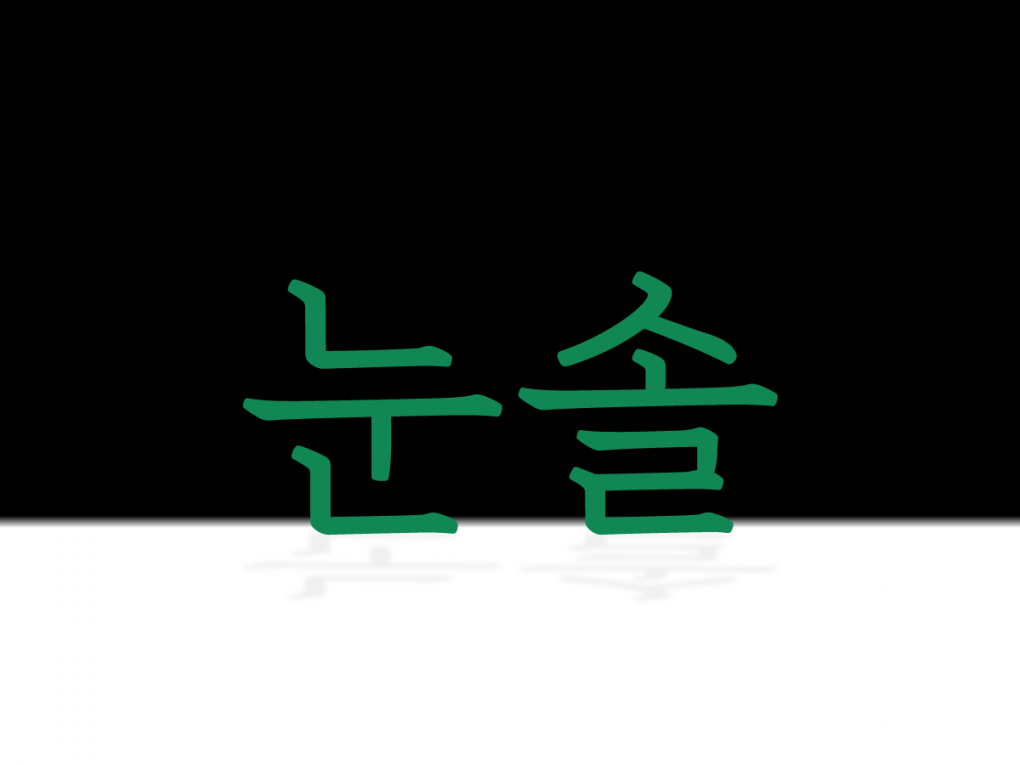
「눈솔」 웨이트 확장에 담긴 숨은 이야기
「눈솔」은 산돌 브랜드사를 이용하는 유저 둘 중 하나는 사용하고 있을 정도로 조용히 강한 폰트입니다. 화려하지는 않지만 묵묵하고 단단한 인상을 가진 「눈솔」 폰트는, 최근 더 넓은 사용성을 위해 확장된 웨이트들로 인사를 드리게 되었어요. (기존 1종(Bold) → 확장 3종(Thin, Regular, Bold))
사실 「눈솔」 폰트는 기획 단계에서부터 3종으로 설계가 되어 있었던 패밀리 폰트였지만, 출시 당시 여건이 되지 않아 1종만 먼저 상용화가 된 아쉬움이 남아 있었던 폰트였죠. 따라서, 「눈솔」 웨이트 확장 프로젝트는 비어있던 퍼즐을 비로소 완성한 프로젝트라 할 수 있겠네요.🙌